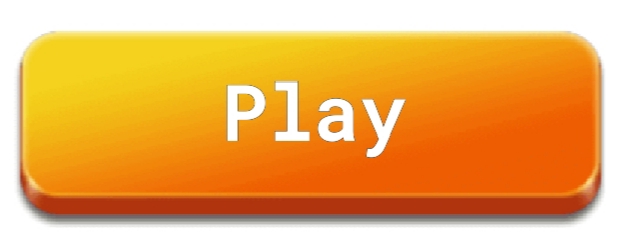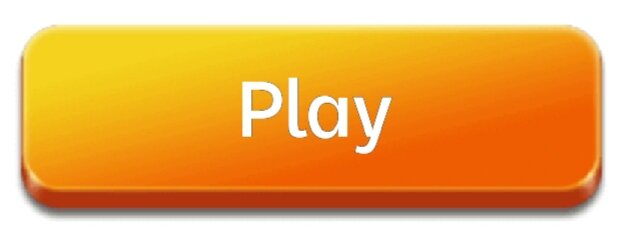
Какой шрифт из данных, на ваш взгляд, лучше?
Первый или второй?
Первый лучше
2 кнопка подходит для игры три вряд какой-то или игры в портретной ориентации, а 1 подходит для игр в альбомной ориентации